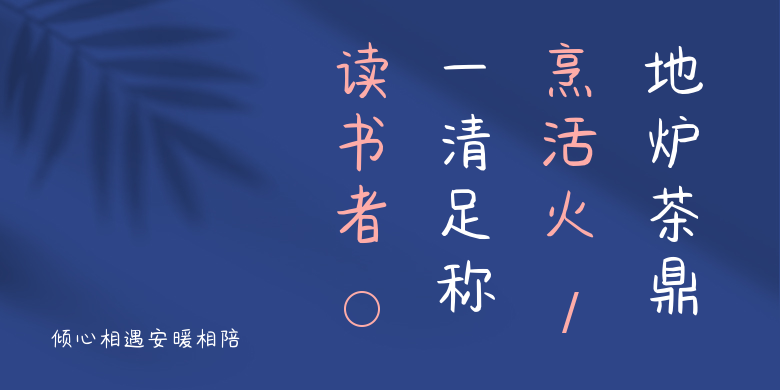
倾心相遇安暖相陪
倾心相遇安暖相陪,这款字体结构工整、笔画清晰,兼顾美观与易读性,适用于标题、正文、海报、包装、LOGO 等多种场景。字形优雅稳定,风格百搭耐看,适配日常排版与创意设计,让文字呈现更舒适、更具质感。倾心相遇安暖相陪一笔一画,皆是细节,以均衡的比例、流畅的线条打造舒适视觉体验,字形端正大气,风格简约现代。无论是商业设计、品牌宣传还是日常排版,都能轻松驾驭,让文字更有格调与力量。倾心相遇安暖相陪字体下载。